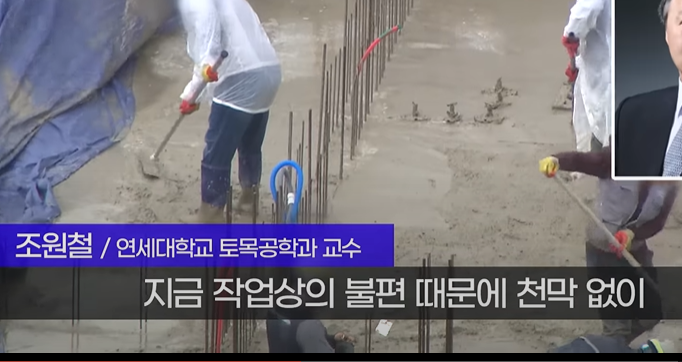
폰트가 뭔지 궁금합니다! tea*** 2023.07.16 글씨체도 눈에 쏙 들어오고 괜찮네요.. 어떤 폰트인지 궁금합니다! 댓글 0 등록 sta*** G마켓 산스 Medium 같네요 https://www.sandollcloud.com/font/15744.html 2023-07-17 답글 달기 tea*** 오 감사합니다! 2023-07-18 답글 달기 댓글 더보기 쉽고 빠르게 가장 비슷한 폰트를 알고 싶다면? 이미지로 검색하기
G마켓 산스 Medium 같네요 https://www.sandollcloud.com/font/15744.html